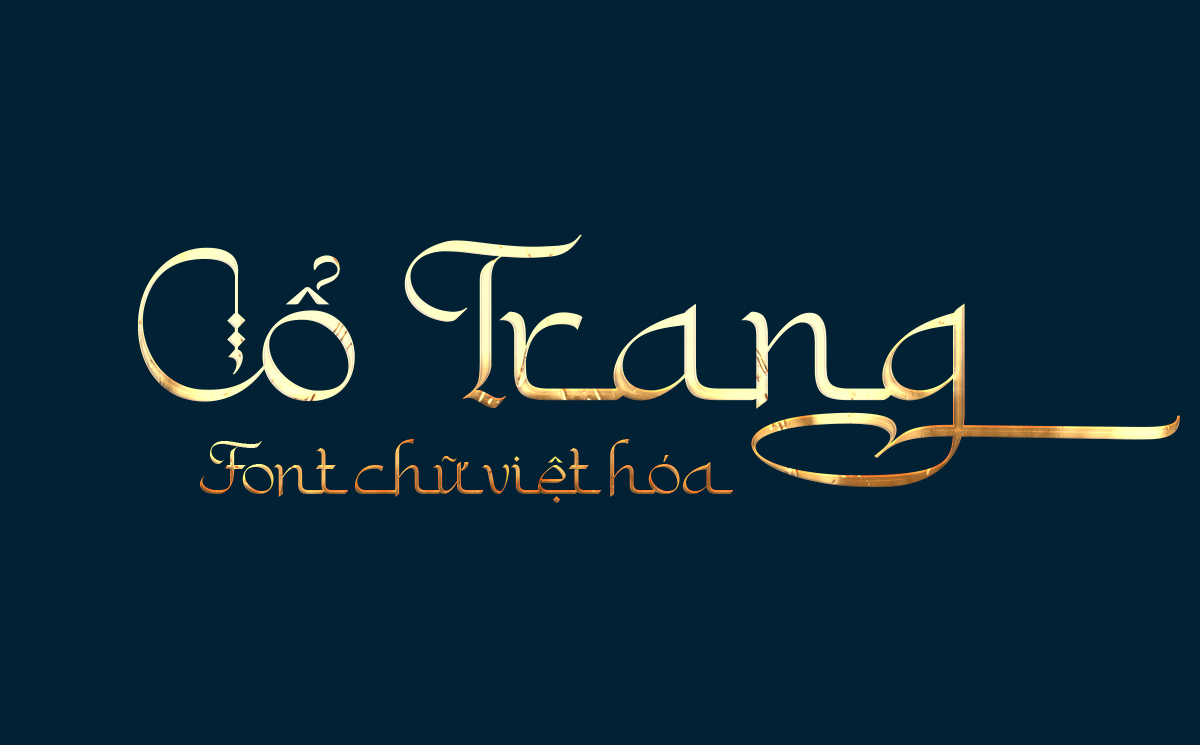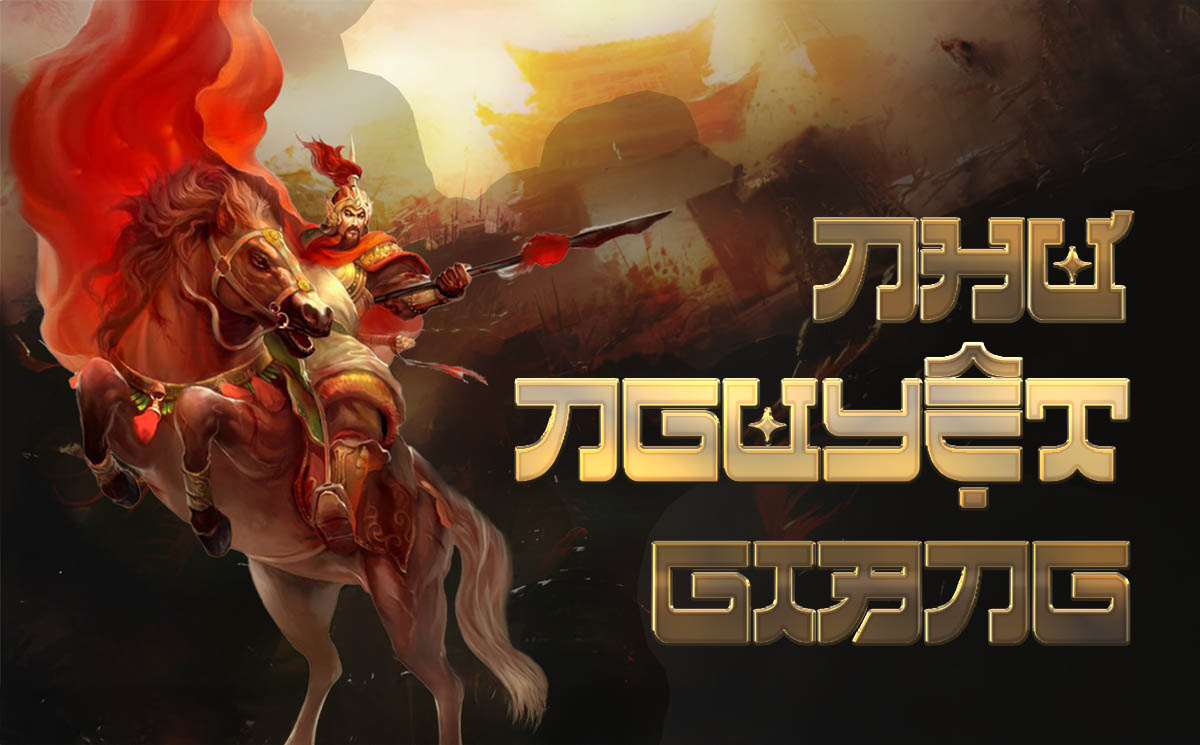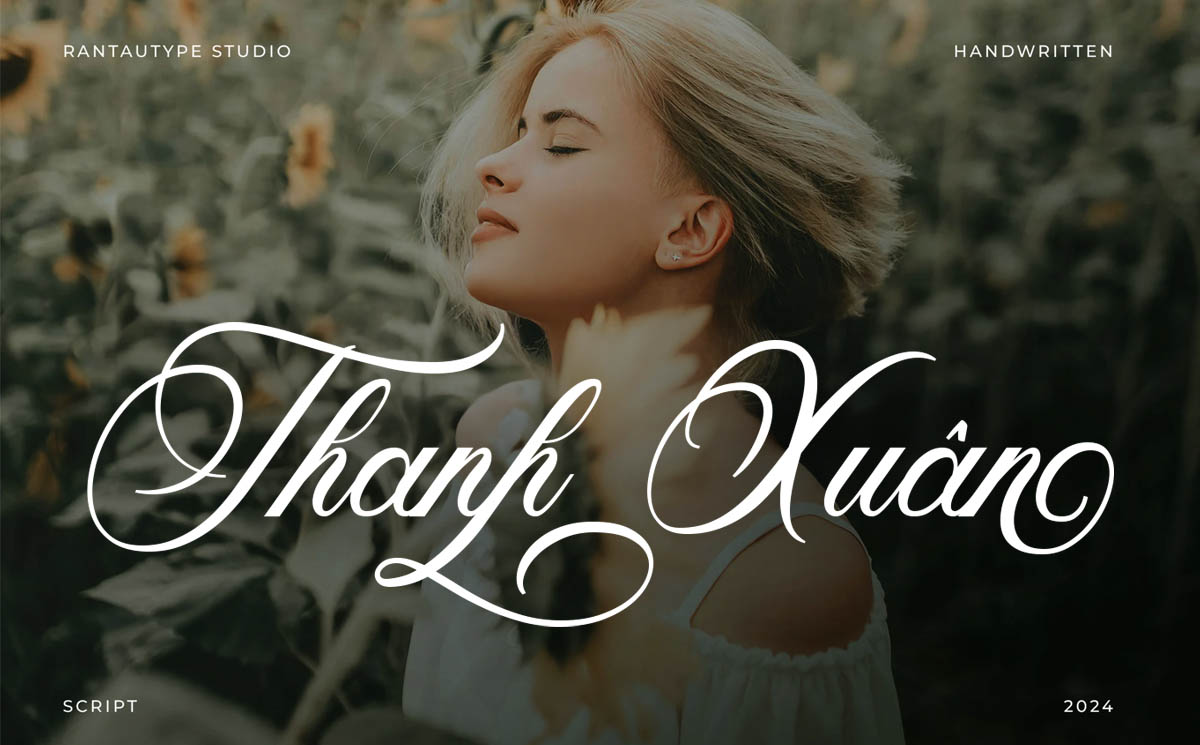
Font chữ tattoo Việt hóa: gợi ý phong cách cá tính, nghệ thuật
Gợi ý font tattoo Việt hóa dòng TH cho thiết kế chữ xăm, logo tattoo studio, poster cá tính, quote nghệ thuật và phong cách calligraphy mạnh.
Font chữ tattoo Việt hóa thường được tìm khi designer cần làm mockup chữ xăm, poster tattoo studio, logo tiệm xăm, quote cá tính, bìa playlist, áo local brand hoặc các thiết kế có tinh thần nổi loạn, nghệ thuật và cá nhân. Khác với font logo thông thường, font tattoo cần có cảm xúc rất rõ: sắc, bay, mạnh, cổ điển, viết tay hoặc có chút bụi.
Tuy nhiên, font tattoo không phải lúc nào cũng phải thật rối. Một chữ xăm đẹp cần đọc được, nhất là khi dùng tiếng Việt có dấu. Nếu font quá nhiều nét nối, dấu có thể bị chồng lên thân chữ. Nếu font quá mảnh, khi in nhỏ hoặc mô phỏng lên da, chữ dễ mất chi tiết. Nếu font quá dày, cụm chữ dài sẽ bị nặng.
Bài viết này gợi ý các font TH Việt hóa phù hợp cho thiết kế tattoo, từ chữ ký mềm, calligraphy mạnh, brush năng lượng, stencil cá tính đến phong cách cổ trang nghệ thuật.
Cách chọn font tattoo Việt hóa
Chọn theo tinh thần chữ xăm
Nếu thiết kế cần cảm giác chữ ký cá nhân, hãy ưu tiên font script hoặc handwritten. Nếu cần phong cách tattoo studio mạnh, hãy dùng calligraphy hoặc brush. Nếu thiết kế nghiêng về nam tính, hành động hoặc streetwear, font stencil và font cứng cáp sẽ hợp hơn. Nếu muốn chất Á Đông hoặc cổ trang, có thể chọn font có sắc thái thư pháp, cổ điển hoặc võ hiệp.
Gõ thử đúng câu tiếng Việt
Không nên chỉ nhìn preview tiếng Anh. Hãy gõ thử chính cụm cần thiết kế như "sống hết mình", "không bao giờ bỏ cuộc", "tự do", "gia đình", "bình an", "dũng khí" hoặc tên riêng có dấu. Với font tattoo, dấu tiếng Việt cần kiểm tra kỹ vì chỉ cần lệch một chút là tổng thể mất tự nhiên.
Dùng font tattoo cho điểm nhấn, không dùng cho đoạn dài
Font tattoo đẹp nhất khi dùng cho câu ngắn, tên riêng, logo chữ, quote hoặc headline. Nếu poster tattoo studio có nhiều thông tin như địa chỉ, lịch booking, giá flash tattoo hoặc điều kiện ưu đãi, phần đó nên dùng font sans-serif rõ ràng hơn.
12 font TH phù hợp cho thiết kế tattoo, chữ xăm và poster cá tính
1. TH Mrattoos Regular - font chữ ký cá tính cho quote và chữ xăm
Bạn có thể dùng TH Mrattoos Regular cho các cụm chữ như "tự do", "bình an", "keep going", "sống thật" hoặc tên khách hàng trong mockup tattoo. Với câu dài, hãy tăng khoảng cách dòng để dấu tiếng Việt không bị bí.
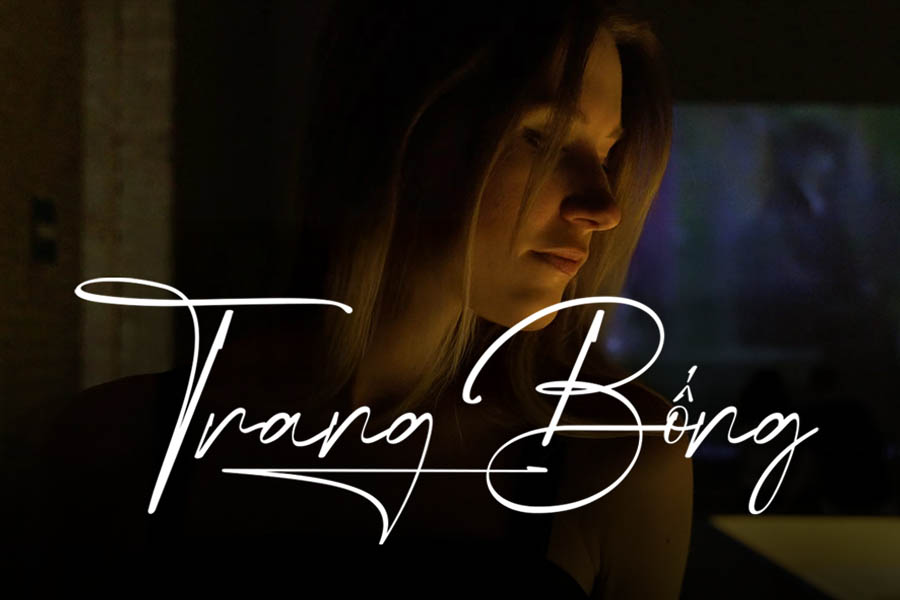
2. TH Chicanos - calligraphy mạnh cho tattoo studio và poster nghệ thuật
TH Chicanos có chất calligraphy nổi bật, phù hợp với poster tattoo, logo studio, bìa album, áo local brand hoặc các thiết kế cần nét chữ có lực và chuyển động. Font tạo cảm giác nghệ thuật rõ hơn nhóm chữ ký mềm.
Với TH Chicanos, hãy dùng cho headline lớn hoặc cụm chữ ngắn. Nếu đặt trên nền texture, ảnh da, nền đen hoặc mockup áo, nên tăng tương phản để các nét bay không bị chìm.
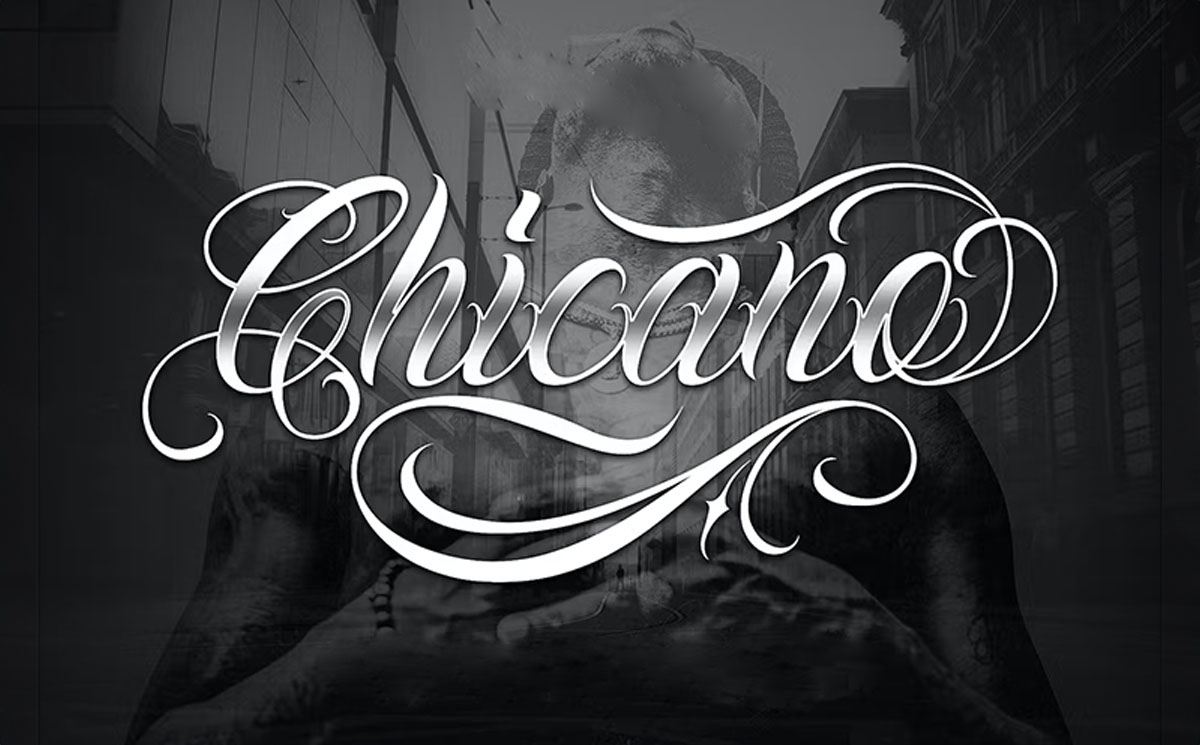
3. TH Signatura - font chữ ký cho thiết kế tattoo tinh tế
TH Signatura phù hợp với phong cách chữ xăm nhẹ, tên riêng, quote cá nhân, chữ ký trên ảnh hoặc logo artist. Font có cảm giác viết tay tự nhiên, hợp với các thiết kế không cần quá dữ nhưng vẫn muốn giữ chất riêng.
Bạn nên dùng TH Signatura cho dòng ngắn và đặt trên nền sạch. Với poster nhiều thông tin, chỉ dùng font này ở phần cảm xúc; thông tin booking và liên hệ nên dùng font phụ dễ đọc.
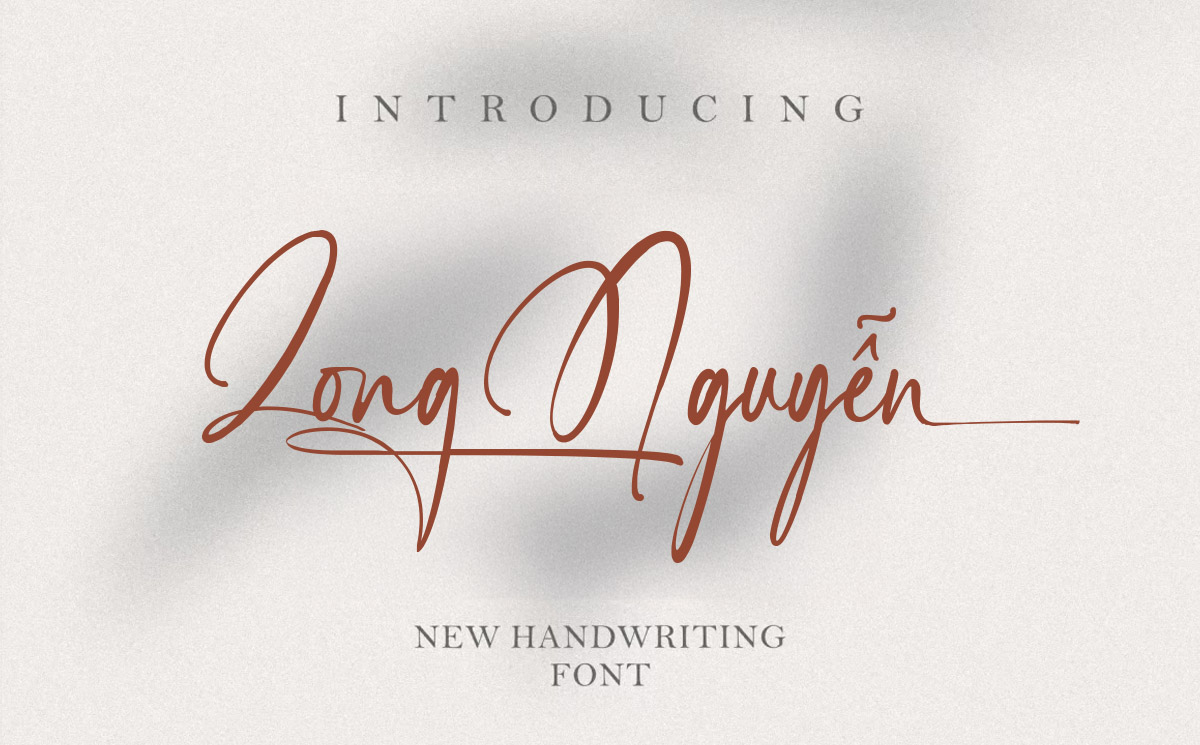
4. TH Jonathan Stattera - nét mảnh viết tay cho tattoo quote
TH Jonathan Stattera có nét mảnh, mềm và giàu cảm xúc, phù hợp với quote tattoo, chữ nhỏ trên ảnh, thiệp cá tính, poster nghệ thuật hoặc chữ ký thương hiệu. Font hợp với các concept tối giản, nhiều khoảng trắng và ít hiệu ứng.
Vì nét chữ mảnh, hãy kiểm tra kỹ khi dùng ở kích thước nhỏ. Nếu làm mockup xăm thật, nên phóng to để xem dấu tiếng Việt và các nét nối có rõ không.
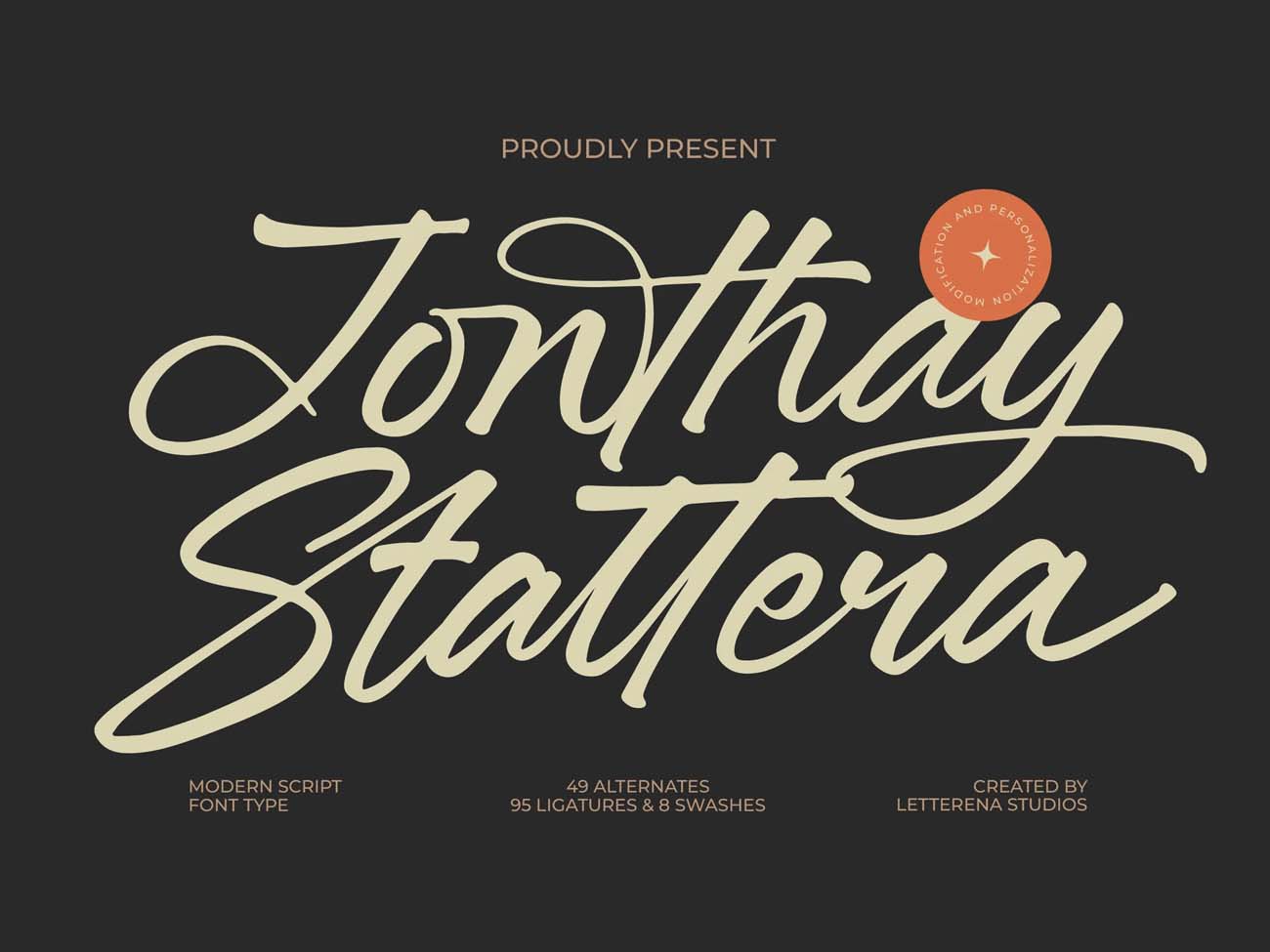
5. TH Hildesheim - script cổ điển cho tattoo vintage
TH Hildesheim mang phong cách script cổ điển, phù hợp với tattoo quote vintage, logo tiệm xăm, poster sự kiện nghệ thuật, nhãn sản phẩm thủ công hoặc bìa album có tinh thần xưa. Font tạo cảm giác trang trọng hơn các font viết tay đời thường.
Bạn có thể dùng TH Hildesheim cho tên studio, câu motto hoặc cụm chữ ngắn. Không nên dùng cho đoạn dài vì script cổ điển cần khoảng thở để đẹp.
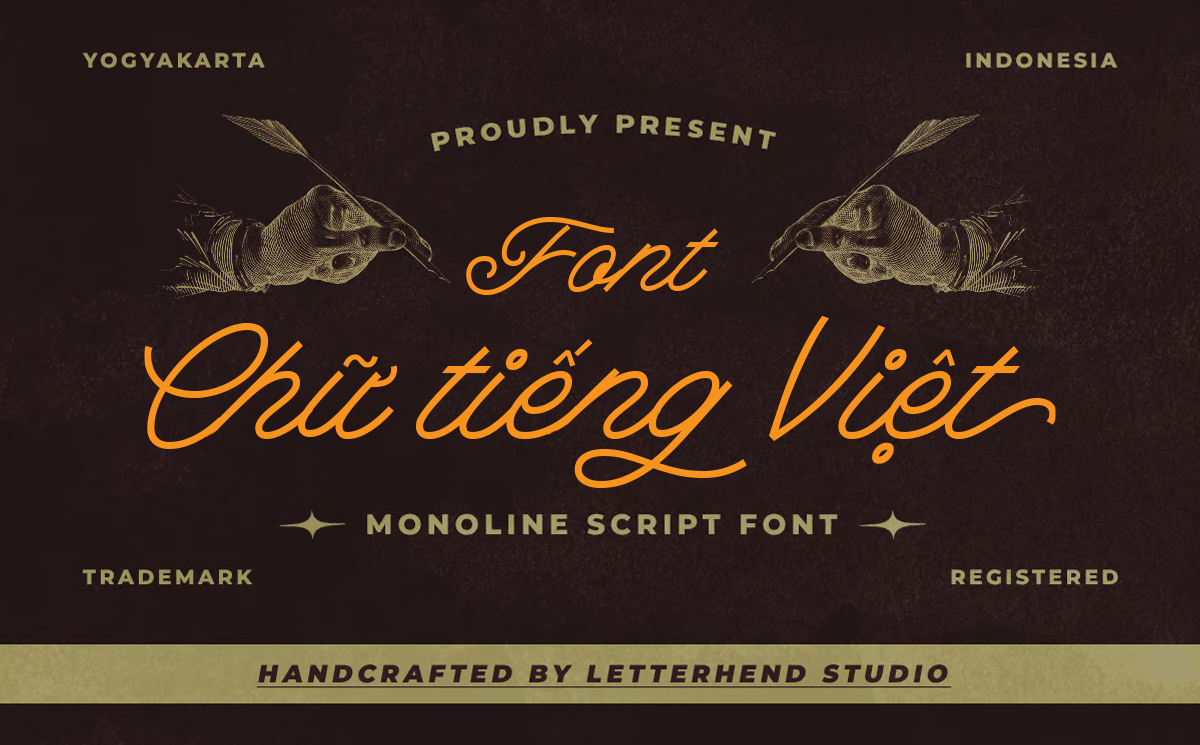
6. TH Boulderstone - calligraphy hiện đại cho thiết kế cá tính
TH Boulderstone có chất calligraphy hiện đại, hợp với poster tattoo, quote mạnh, thiết kế áo, nhãn sản phẩm cá tính hoặc social post của tattoo artist. Font có chuyển động tốt nhưng không quá cổ.
Khi dùng TH Boulderstone, hãy giữ headline ngắn. Font rất hợp với các cụm như "born free", "stay wild", "khác biệt", "không khuất phục" hoặc tên bộ sưu tập flash tattoo.